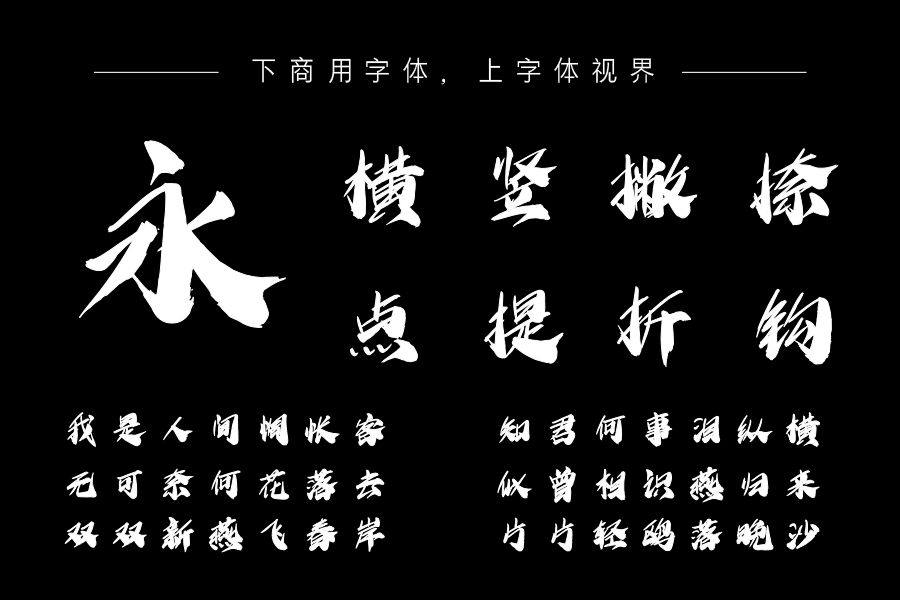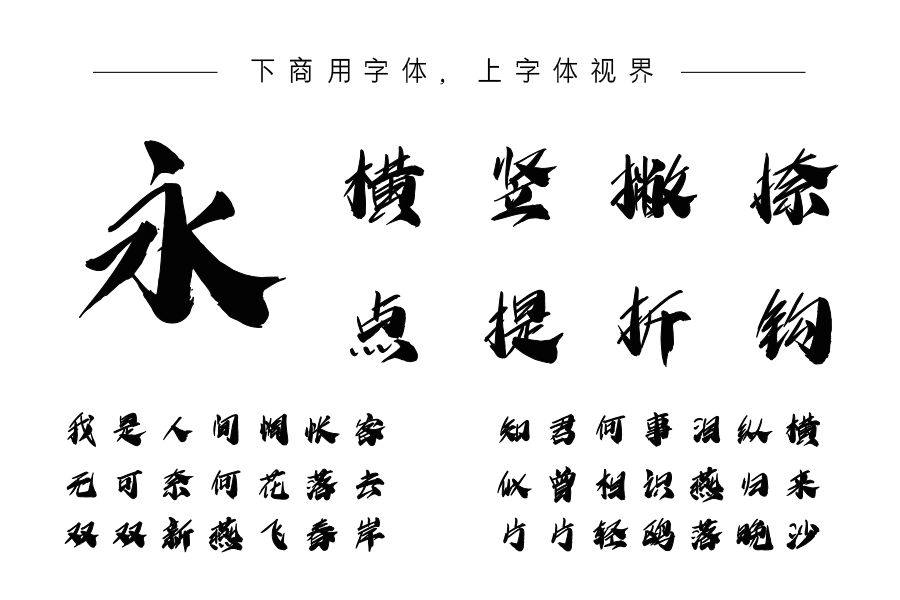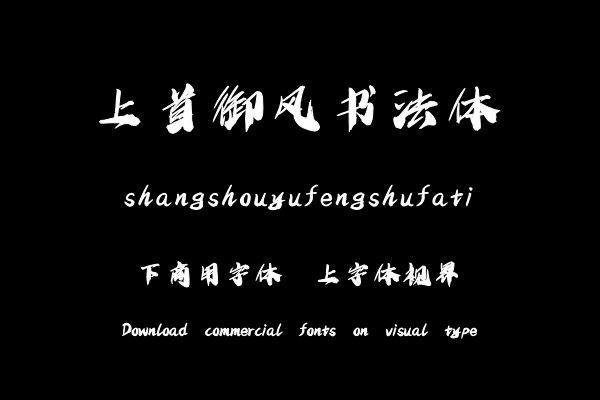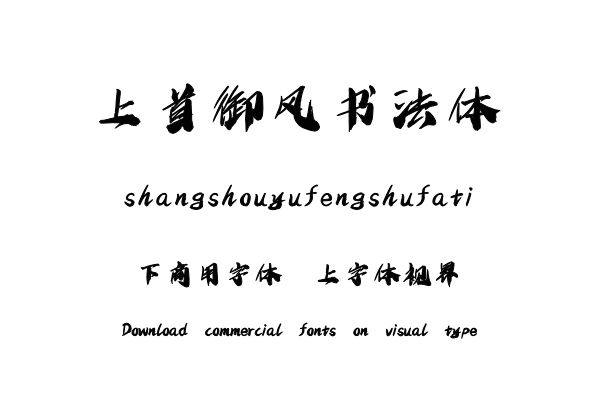
上首御风书法体,字体笔势潇洒飘逸灵动,随风飘荡,张力十足,动静结合,粗细对比强烈,更有视觉冲击,更加突出主题,让人印象深刻。适用于搭配标志、广告标语、商业广告等......购买须知:“下载服务费”与“字体VIP”所获得字体 仅用于个人非商用, 商用请联系付费授权。本字体为电脑用字,手机没有root权限不支持直接手机换字(手机如何root,请自行百度搜索教程)。购买前请先 了解清楚后再付款 ,字体为虚拟产品无法回收 一旦购买不支持退款。